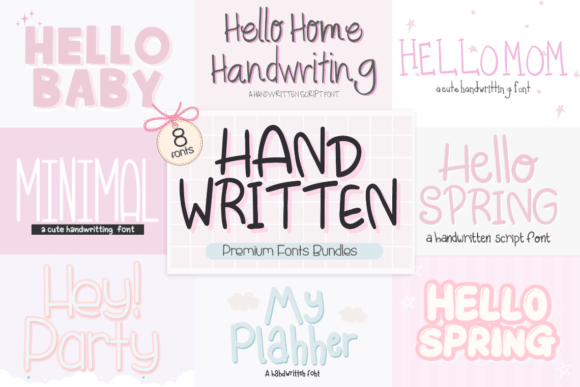
Spring, Handwritten Bundles
Ulasan Lengkap Spring Handwritten Bundles – Font yang Membawa Keceriaan Musim Semi
Jika Anda sedang mencari font handwritten yang modern, elegan, dan penuh pesona untuk proyek kreatif Anda, Spring Handwritten Bundles adalah pilihan yang tak boleh dilewatkan. Paket ini menyajikan koleksi huruf tangan yang dirancang khusus untuk menambahkan sentuhan musim semi pada setiap desain, mulai dari poster hingga kartu ucapan.
Kenapa Spring Handwritten Bundles Layak Dipilih?
- Desain Serbaguna: Cocok untuk poster, undangan, header, judul, kartu ucapan, dan lettering.
- Gaya Modern & Elegan: Kombinasi antara kesan alami tulisan tangan dan detail tipografi kontemporer.
- Kualitas Tinggi: Setiap huruf didesain dengan ketelitian tinggi, memastikan tampilan bersih dan profesional.
Pengalaman Menggunakan Spring Handwritten Bundles
Saat pertama kali menguji paket ini, saya langsung merasakan kehangatan yang ditawarkan oleh setiap varian font. Garis-garisnya yang halus namun penuh karakter membuat judul poster menjadi lebih hidup, sementara gaya yang lebih lembut sangat ideal untuk kartu ucapan dan undangan pernikahan. Kombinasi variasi tebal dan tipis dalam satu paket memberi kebebasan untuk bermain dengan hierarki visual tanpa harus mencari font tambahan.
Manfaat Utama untuk Proyek Anda
- Meningkatkan Daya Tarik Visual: Font yang tepat dapat membuat desain Anda lebih menonjol di antara ribuan karya lain.
- Menghemat Waktu: Semua varian sudah tersedia dalam satu bundle, mengurangi kebutuhan untuk mengunduh atau membeli font terpisah.
- Menambah Sentuhan Personal: Tulisan tangan memberikan nuansa personal yang sulit dicapai dengan font standar.
Kesimpulan – Apakah Spring Handwritten Bundles Worth It?
Jawabannya sangat YA. Dengan kombinasi estetika modern, fleksibilitas penggunaan, dan kualitas tinggi, Spring Handwritten Bundles menjadi investasi yang cerdas bagi desainer grafis, pemilik bisnis, atau siapa saja yang ingin menambahkan sentuhan springtime charm pada karya mereka. Dapatkan sekarang dan ubah setiap proyek menjadi perayaan keindahan musim semi yang penuh gaya.